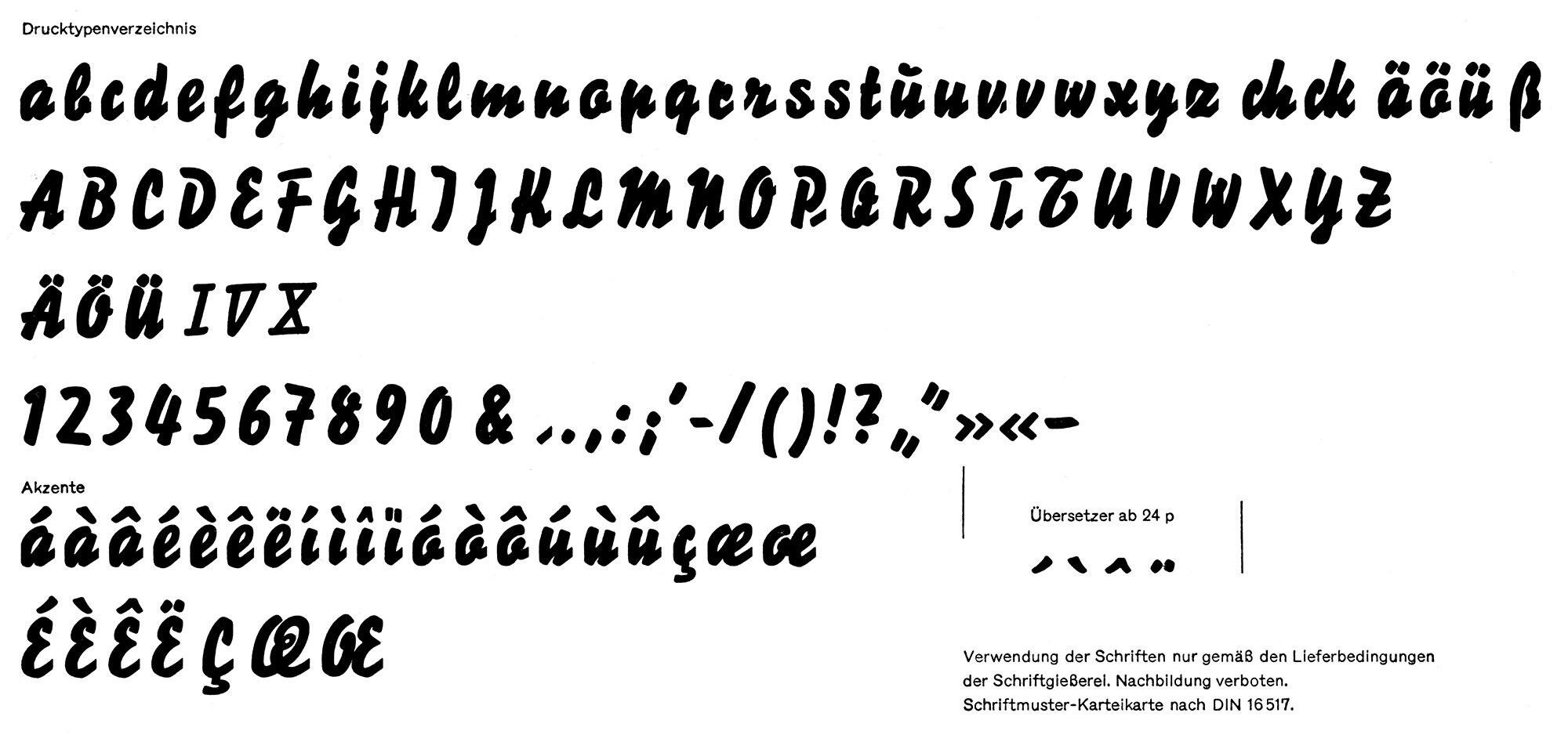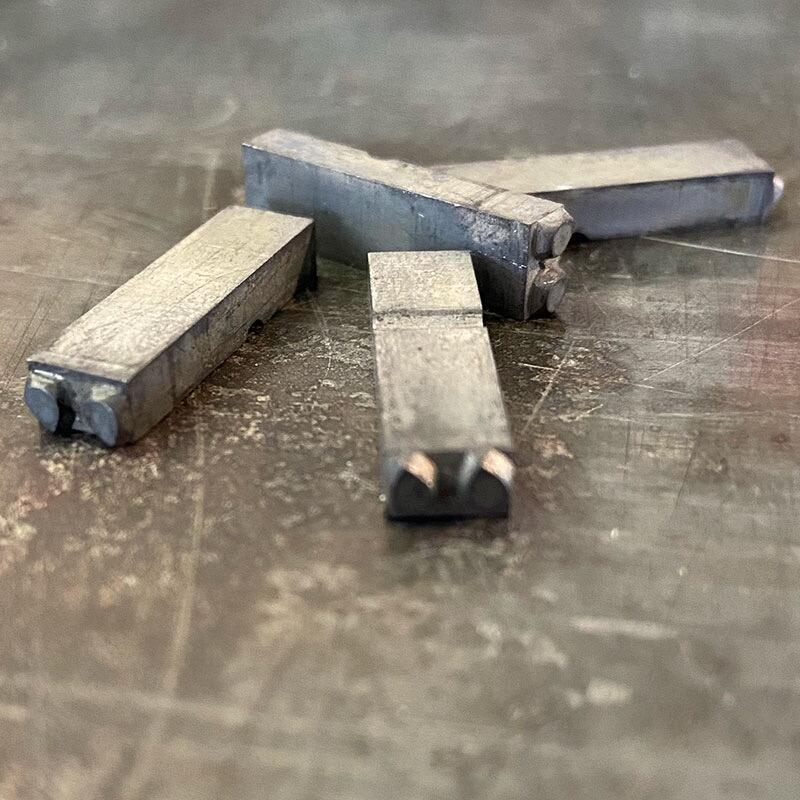
Übersetzer nennt man im Bleisatz die diakritischen Zeichen, welche Versalien größerer Schriftgrade zu Umlaut- und Akzentzeichen verwandelten. In einigen Schriften wurden zusätzlich Kleinbuchstaben in verkürzter Größe geliefert, die zur Aufnahme dieser Übersetzer bestimmt waren.
Übersetzer – Bedeutung/Definition